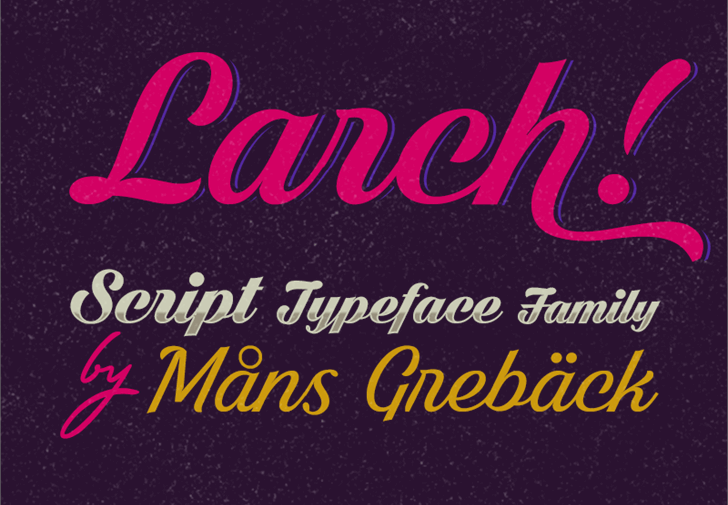
Bright Larch Font – Download Grátis
Aqui está uma descrição para a página de download da fonte “Bright Larch Font” no formato pedido: Envolvente e natural, a fonte “Bright Larch” é perfeita para quem procura uma fonte script elegante e versátil. Desenvolvida pelo talentoso designer Måns Grebäck, esta fonte oferece um toque de elegância que se adequa perfeitamente tanto aos projetos pessoais quanto aos comerciais. A “Bright Larch Font” é ideal para texturas gráficas sofisticadas e criação de identidades visuais. Suas formas fluidas e curvas suaves conferem ao texto uma aparência moderna e contemporânea, sem perder o charme tradicional dos designs de estilo script. Para adicionar um toque extra a seu design, Måns incorporou a capacidade de criar swashes simplesmente digitando # após letras minúsculas ou % após as letras b, d, f, h, i, j, k, l e t para swashes à esquerda. Isso adiciona um toque único e diferenciado às suas criações, tornando a “Bright Larch Font” uma opção irresistível para quem busca uma fonte de alta qualidade que pode se adaptar tanto aos detalhes individuais quanto ao design em massa. Com sua versão personalizada fácil de usar, você pode explorar inúmeras possibilidades criativas com esta “Bright Larch Font”, tornando-a um investimento valioso para qualquer designer gráfico.
Designer: Måns Grebäck